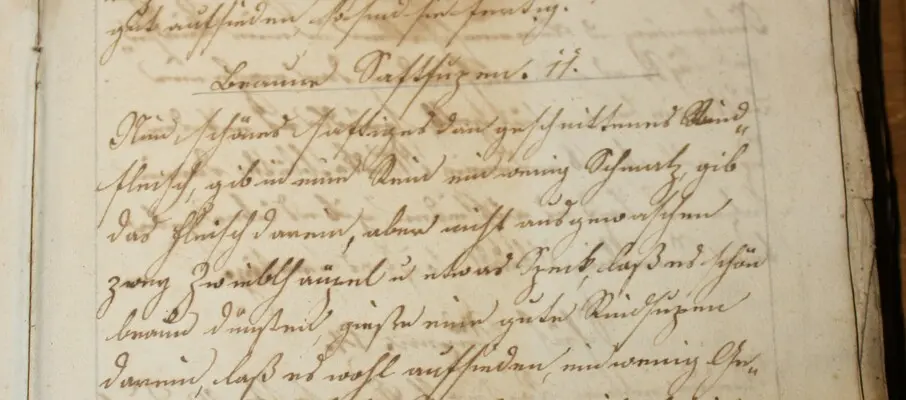
Kurs für deutſche Schrift in St. Ingbert/Saarland
Kursleiter Stephan Weidauer widmet ſich v. a. der Weitergabe der ſchönen alten deutſchen Schrift. Er gibt Kurſe, leitet die Saarbrücker Gruppe „Deutſche Schrift“, iſt Mitglied im Bund für deutſche Schrift e.V. (BfdS) und bei den Freunden der Kurrentſchrift (DKS). In der Fachzeitſchrift „Die deutſche Schrift“ ſchreibt er Artikel und betreut seit 2017 die Buchbeſprechungen.